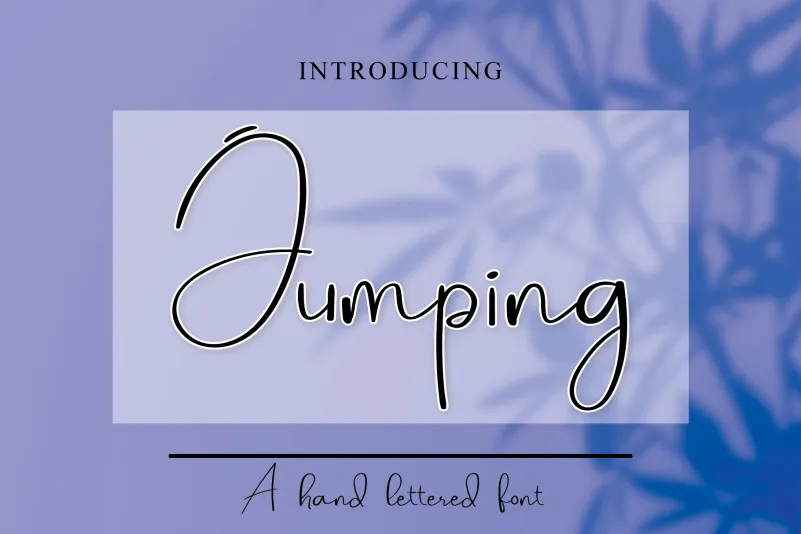
Jumping Font – Download Grátis
Esta é uma fonte escrita a mão com traços finos e elegante, adequada para estilos modernos e sofisticados. Com seu charme próprio, esta fonte se destaca não apenas como um recurso útil em qualquer projeto editorial, mas também como uma ferramenta capaz de dar vida à sua arte visual. Perfeita tanto para títulos quanto para subtítulos e textos detalhados, a Jumping Font oferece um toque único que eleva qualquer design ao nível superior. Com o designer Erik Studio no comando, esta fonte escrita a mão atinge perfeitamente o equilíbrio entre personalidade e elegância. Seja você um profissional de design ou uma estilista de moda, essa fonte é ideal para tornar seus trabalhos ainda mais singulares, oferecendo ao mesmo tempo facilidade de uso em qualquer projeto. Não importa qual seja seu propósito criativo, esta fonte escrita a mão manterá sua identidade única e seu design moderno intactos.